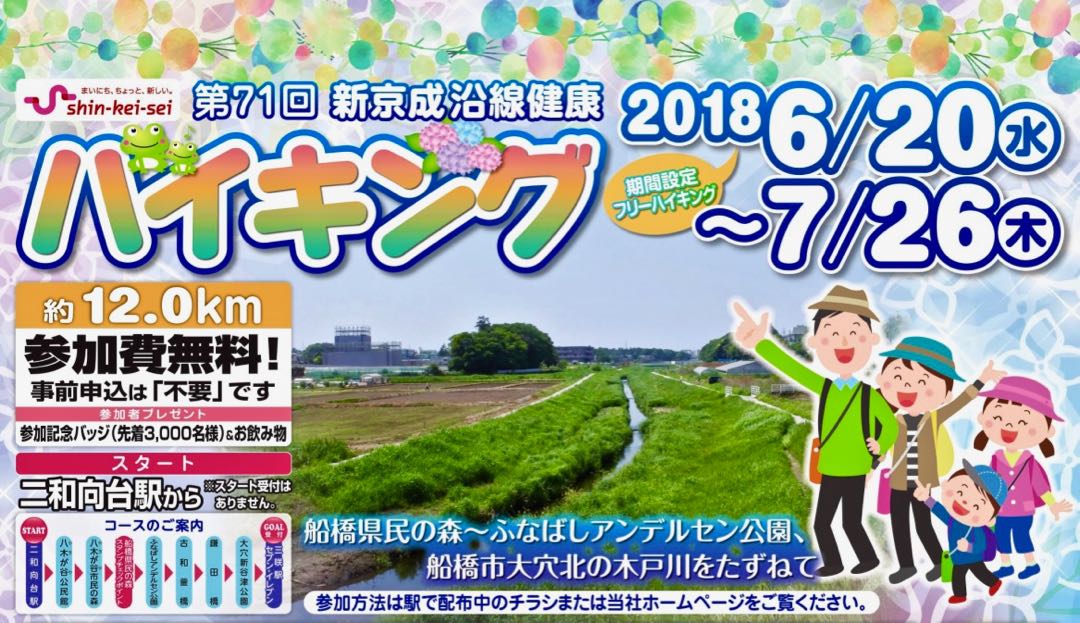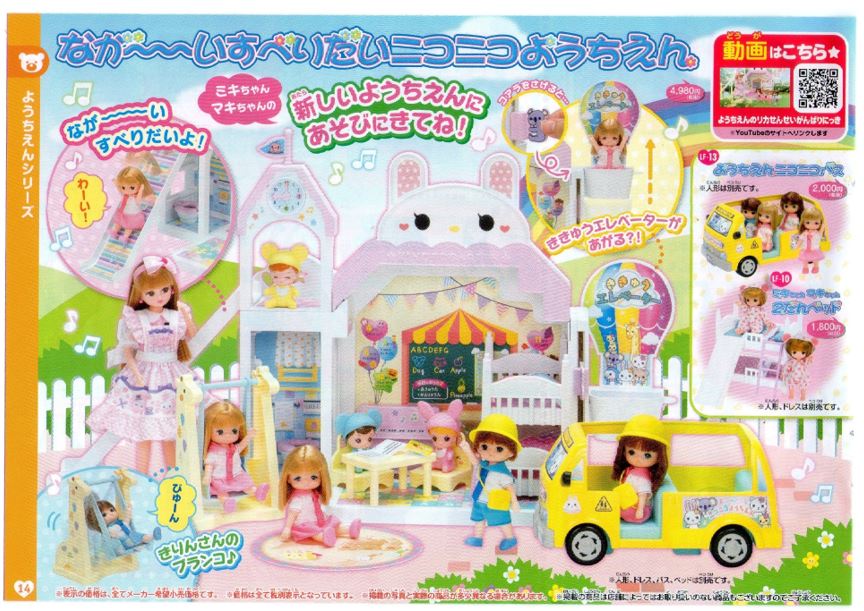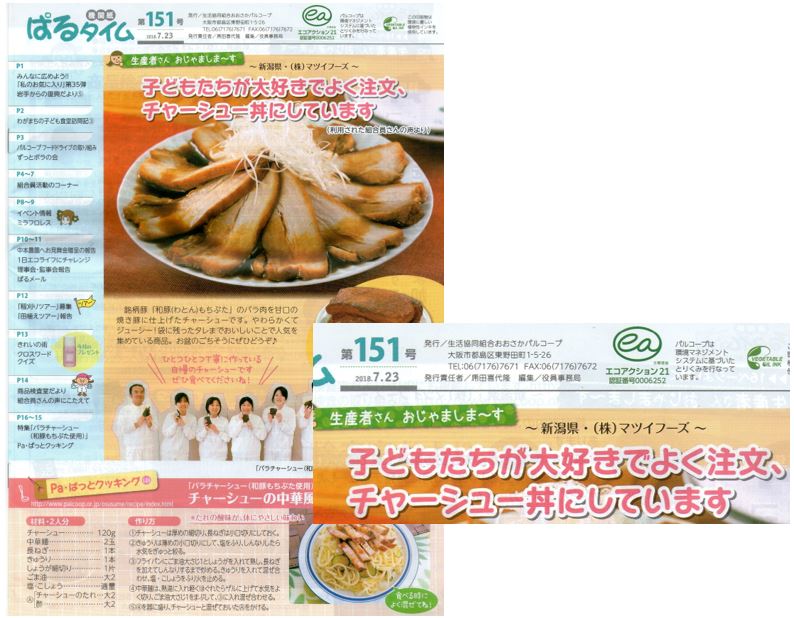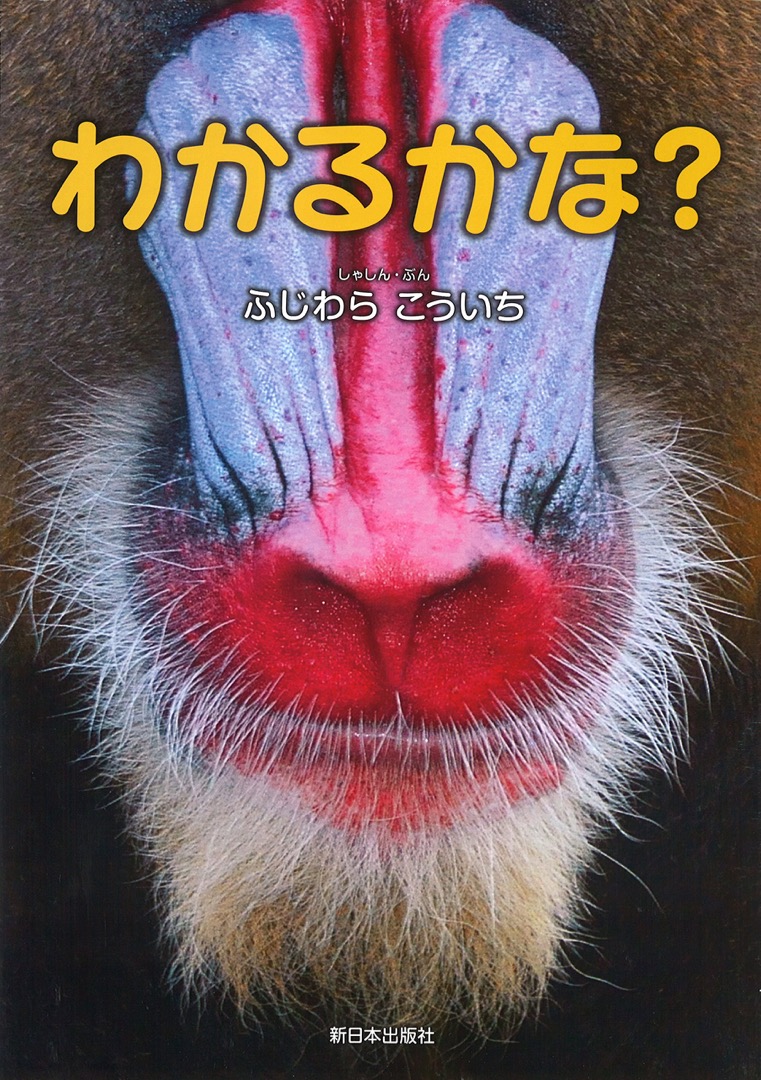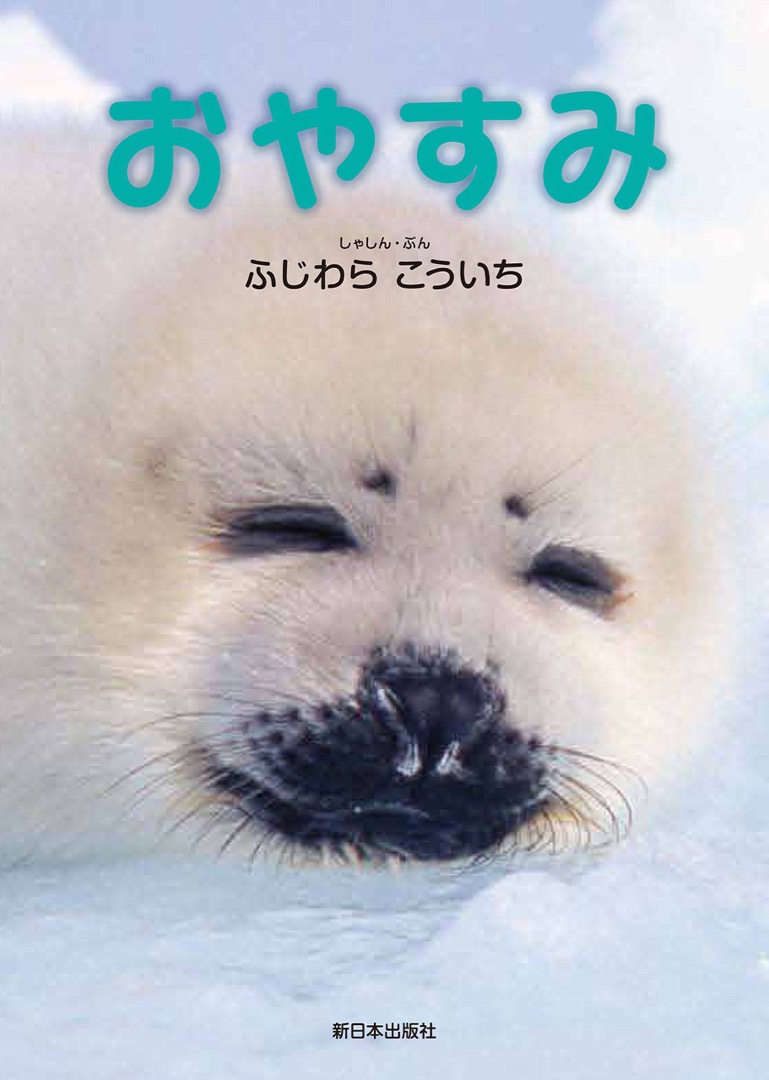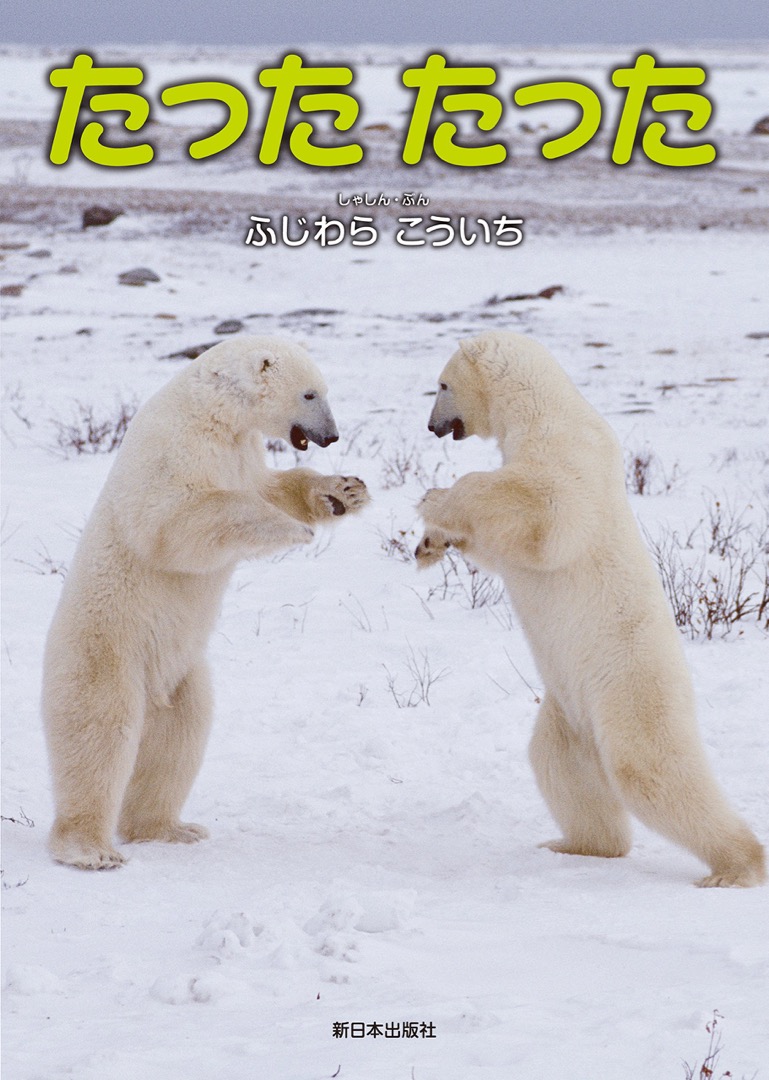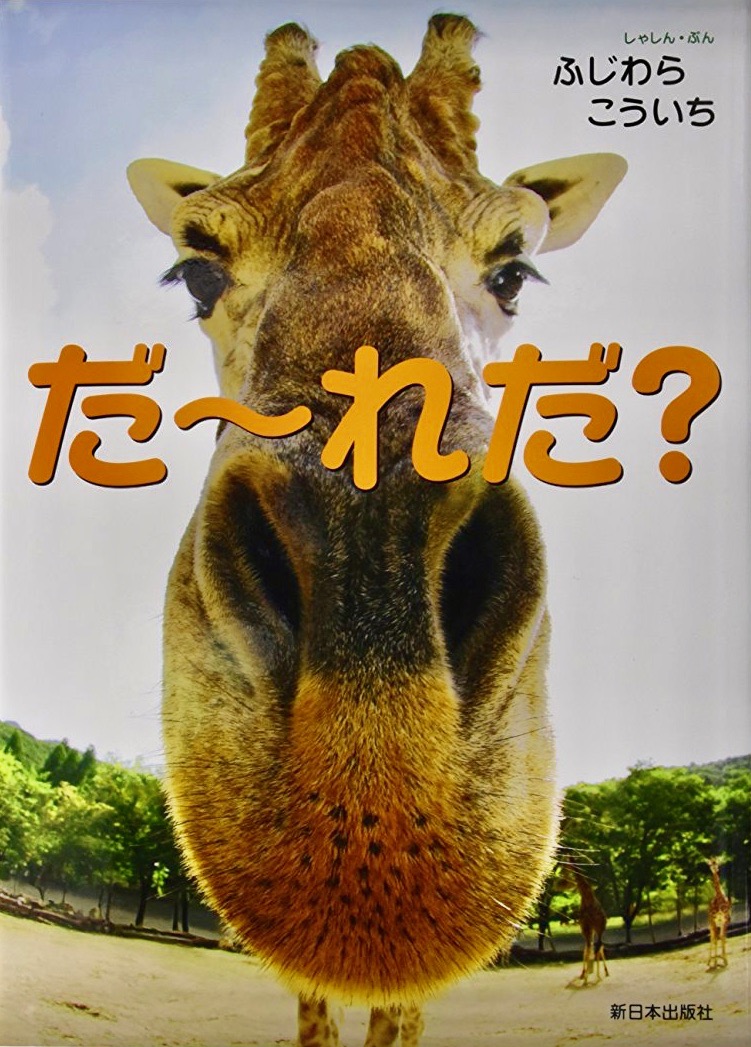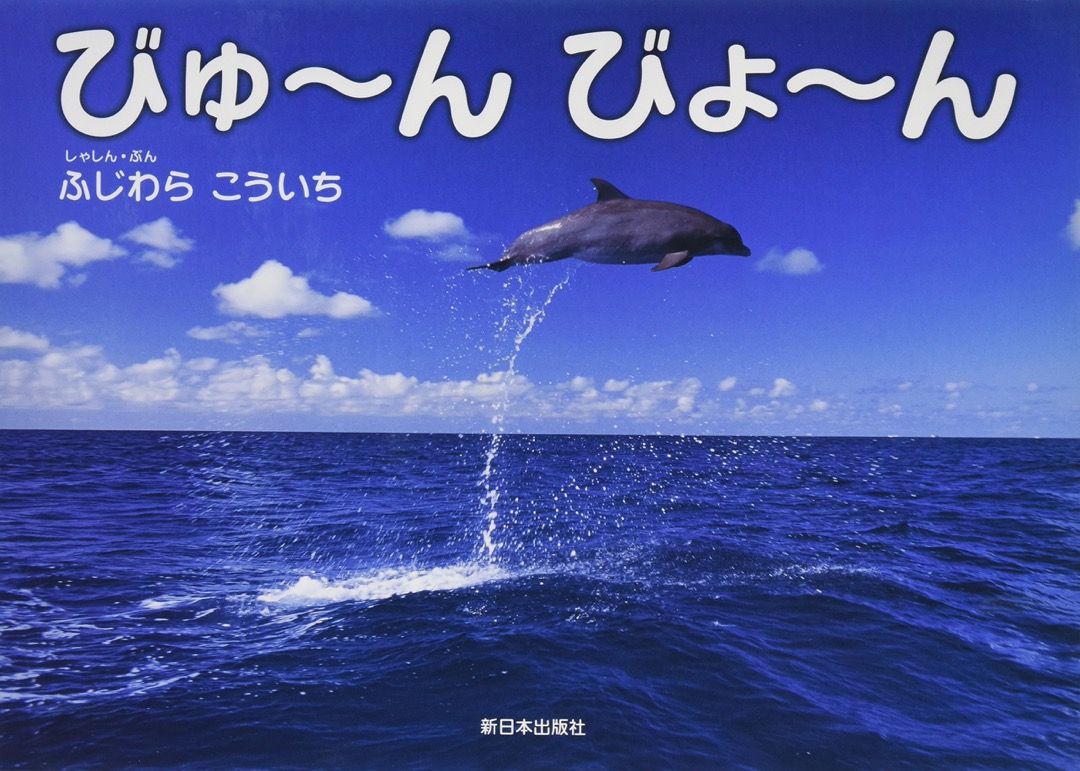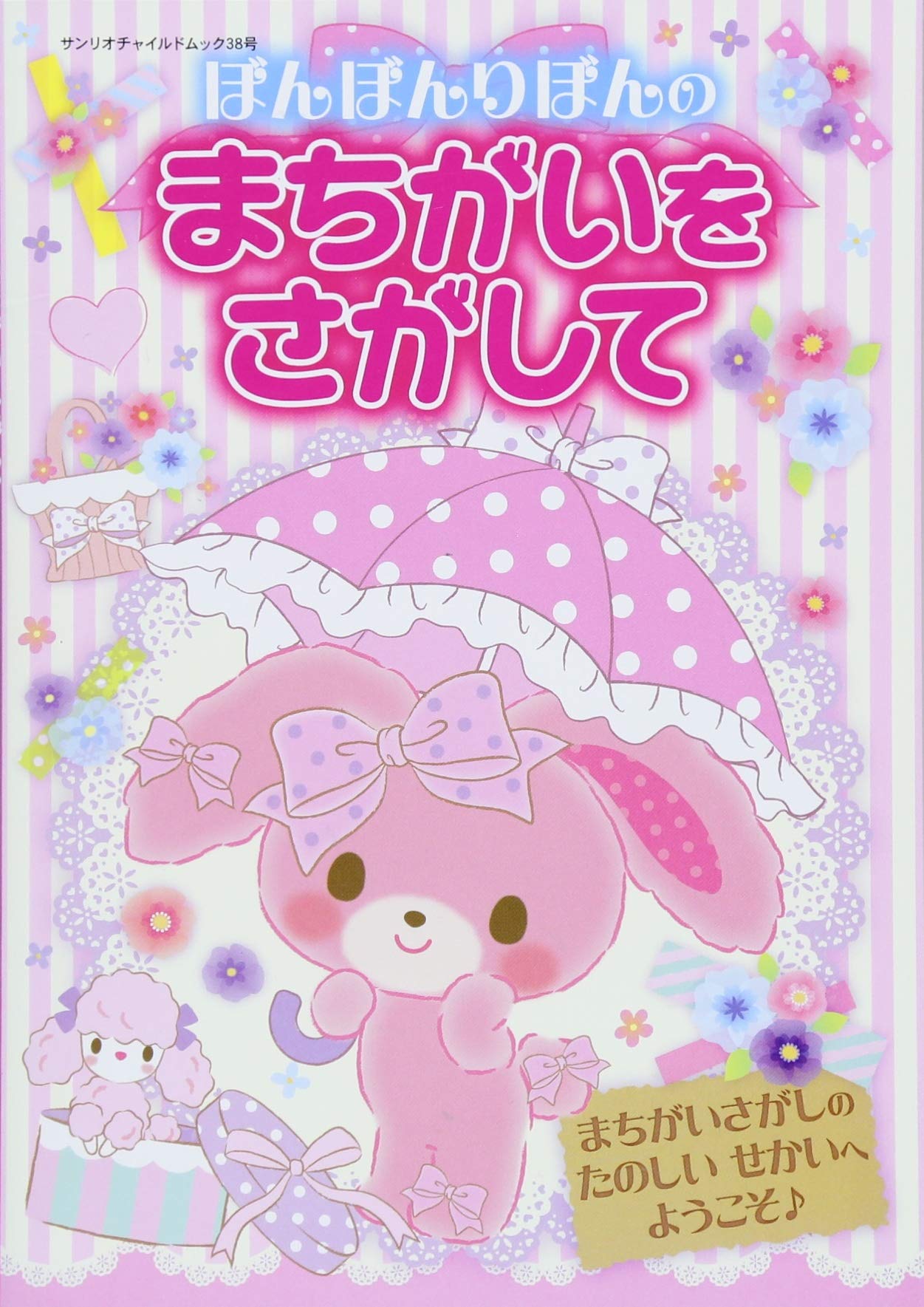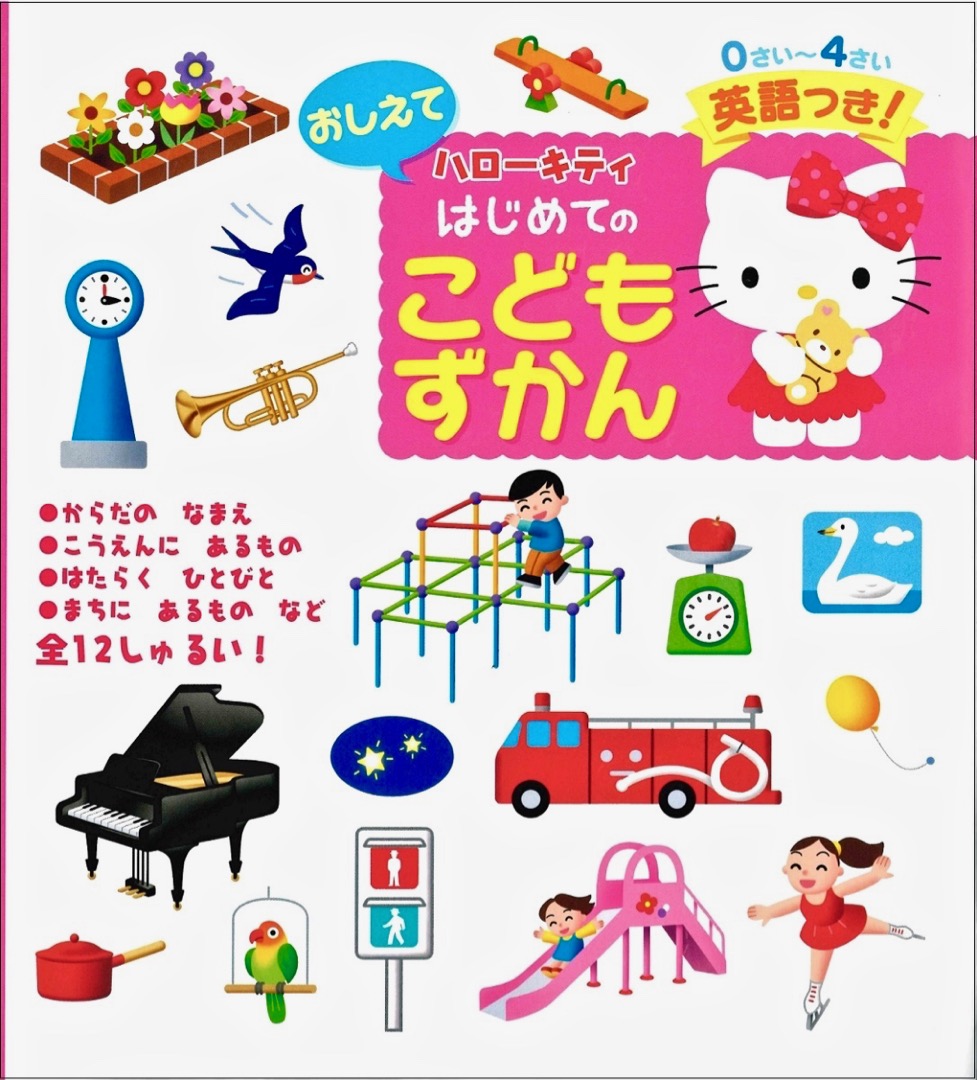
書名:おしごと シールえほん
著者:グループ コロンブス、これきよ
発行:講談社
引っ越しのため、整理をしていた時に出てきたポケットティッシュの袋でキャピーが使われていました。
赤くて太い縁の付いた文字ですね。
キャピー可愛いですよね。
3月7日に発売されるニンテンドー3DSソフト『毛糸のカービィ プラス』の公式サイトで太いキャピーが使われています。
参考にもう1枚。
追加。
これは、製品パッケージの裏面です。
既に投稿したキャピー(M社)と異なり、こちらはF社に提供されているキャピーのようです。
生協おおさかパルコープの機関紙「ぱるタイム」1月28日号です。
最終面(16面)での企画「生産者さん おじゃましま〜す」での記事見出しで使用しています。
1月から始まった地元(J:COM)のローカル番組『いけるやん!』でキャピーが採用されていました。
F社に提供されているものですね。
ハッピーと骨格は同じでも、全く違う印象なのが楽しいです。
参考画像をもう1枚。
タイプラボフォントはテレビでよく見かけるのですが、記録するのが面倒でね…。
とっさに画面撮影していただいての投稿、助かります。
大阪の、生協おおさかパルコープの機関紙12月号での使用。
上の「たまごがふわふわ〜」の見出し。下の連載のタイトルも。
大阪市平野区のSS書籍売り場で見つけました。
「ミニオンズ!さがして!みつけて!」
発行・小学館
A4変形
子ども向けの書籍。
大阪府の、富田林市など6市1郡の南河内地域をエリアとして発行されている生活提案情報紙12月号の連載で使用されています。
大阪市の、生協おおさかパルコープの機関紙第155号(11月19日)の最終面「生産者さん おじゃましま〜す」の欄の見出しで使用されています。
「かずのこ、やっぱり〜」の部分です。
ライセンスされたもののようです。
さとうゆたか  2018年11月26日(月) 8:06 [修正]
うめ吉さん、投稿ありがとうございます。
えほん  さとうゆたか  2018年11月17日(土) 9:00
書名:ねむいんだもん
著者:福田幸広、ゆうきえつこ
発行:そうえん社